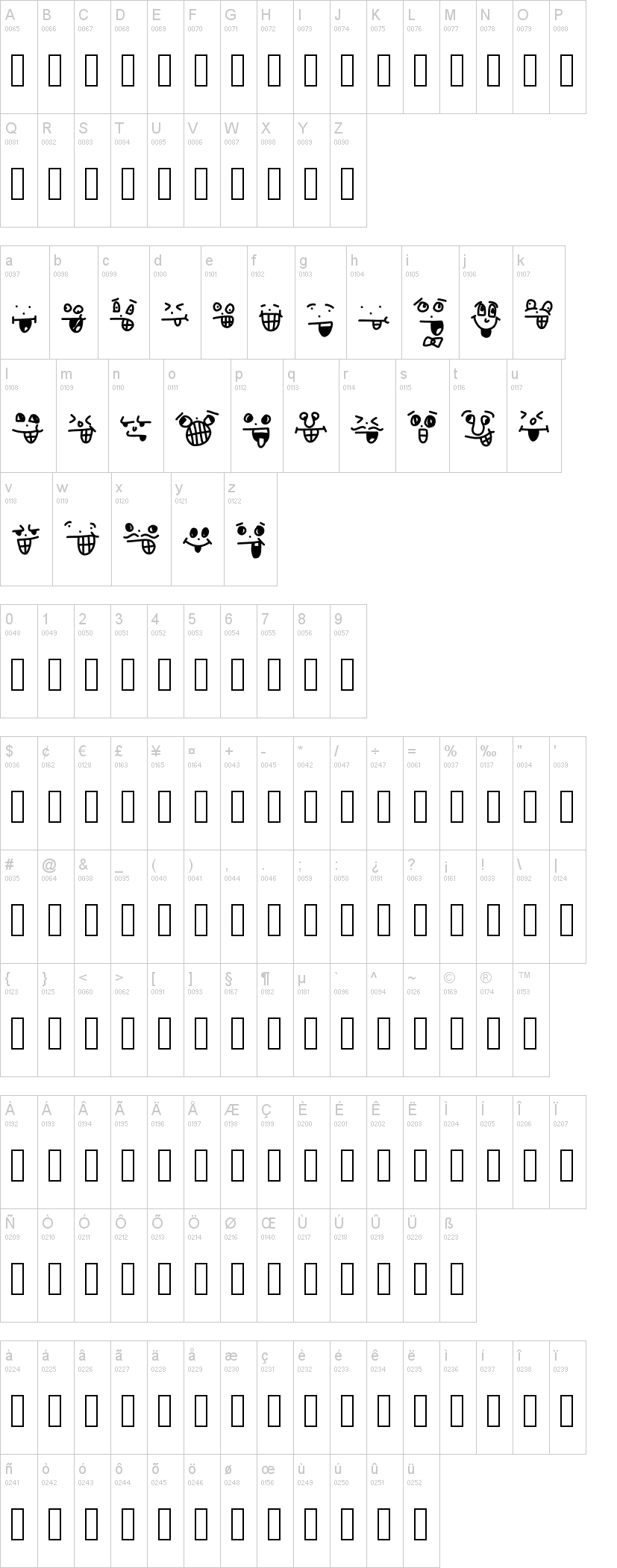
Crazy Smile 字体是一款卡通字体,由著名字体设计师Aaron Amaral设计,它具有轻松、活泼和有趣的设计风格。它的字体设计具有强烈的节奏感,在文字中增添了许多有趣的设计元素,如花纹、简约的花纹、折线以及圆形图案等,使文字变得更加有趣和动感。Crazy Smile字体可以用于各种印刷品、网页、海报、标志等,可以为文字增添更多的趣味性和视觉效果。内容介绍
Crazy Smile是一款非常不错的手写艺术字体,具有很好的视觉感,适合于文化类的宣传设计、商业类品牌的广告和产品包装设计以及个性化文字排版等较多场景。